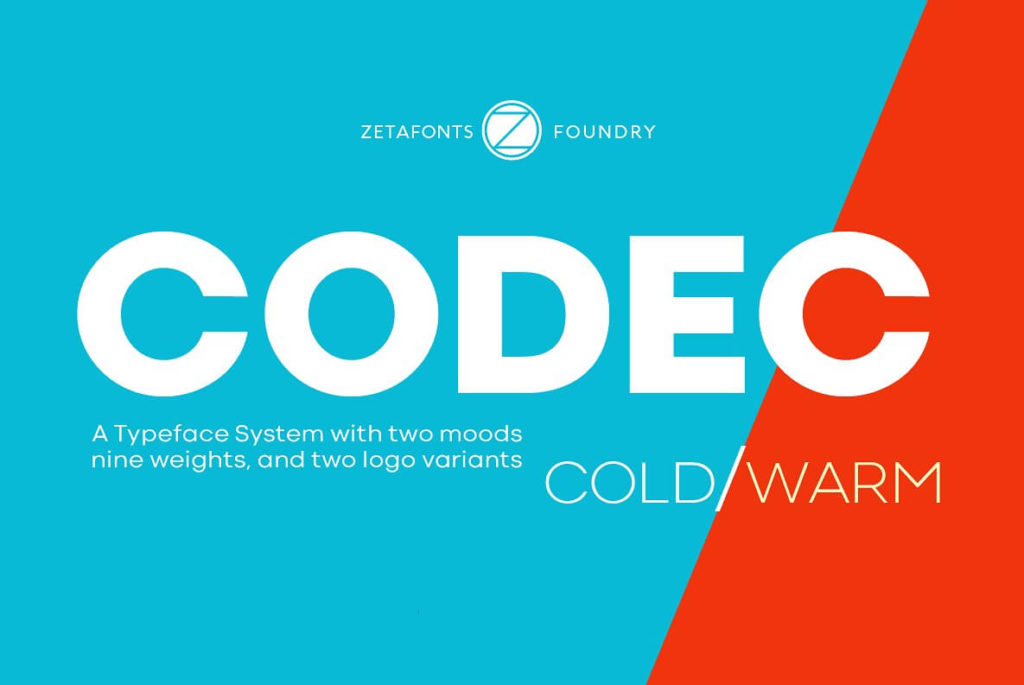
Шрифт Codec — 44 s
Шрифт Codec — это геометрическая гротесковая система, разработанная дизайнерами Франческо Кановеро, Козимо Лоренцо Панчини и Андреа Тартарелли для словолитни Zetafonts в 2017 году . Особенность шрифта Codec — это два контрастных варианта, построенных на одном каркасе: Codec Cold и Codec Warm . Семейство насчитывает 44 начертания . Поддерживает кириллицу, что делает его отличным выбором для проектов на русском языке, где нужна современная, гибкая и технологичная типографика. Оцените его возможности, и если вы ищете универсальный шрифт с характером, вы можете скачать пробную версию для ознакомления прямо с этой страницы .